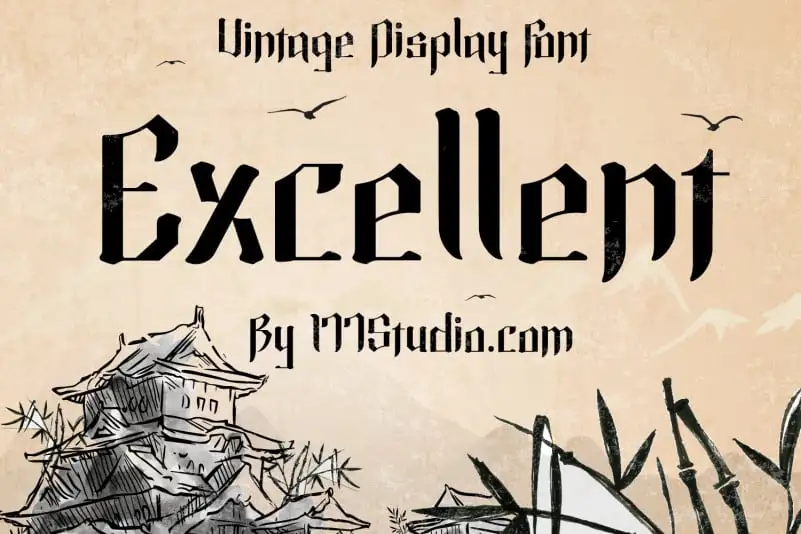
Excellent Display Font – Fonte Grátis
Excellent Display Font
A fonte ‘Excellent Display Font’ oferece um estilo vintage, caracterizado pela influência do blackletter moderno. Esse tipo de fonte foi projetada com carinho para dar à sua obra aquela sensação orgânica e quase desenhada a mão. É perfeitamente adequado para vários usos criativos e práticos em seu projeto. Seja você um designer que está buscando uma maneira única de trazer vida às suas idéias, ou alguém que busca dar um toque moderno a mensagens digitais tradicionais, ‘Excellent Display Font’ é a escolha perfeita. É especialmente adequado para o headline, menus, logotipos, rótulos, sinalizações, citações e até mesmo os famosos posters urbanos. Seu design estiloso e único funcionará em uma variedade de contextos e garantirá que seu trabalho tenha aquela sensação orgânica quase desenhada a mão. Aproveite essa fonte para dar um tom ainda mais especial às suas criações, seja ela uma peça de arte impressa ou um design digital. Com ‘Excellent Display Font’, você pode garantir que sua obra prima terá aquele toque único que tornará seu trabalho singular e memorável.